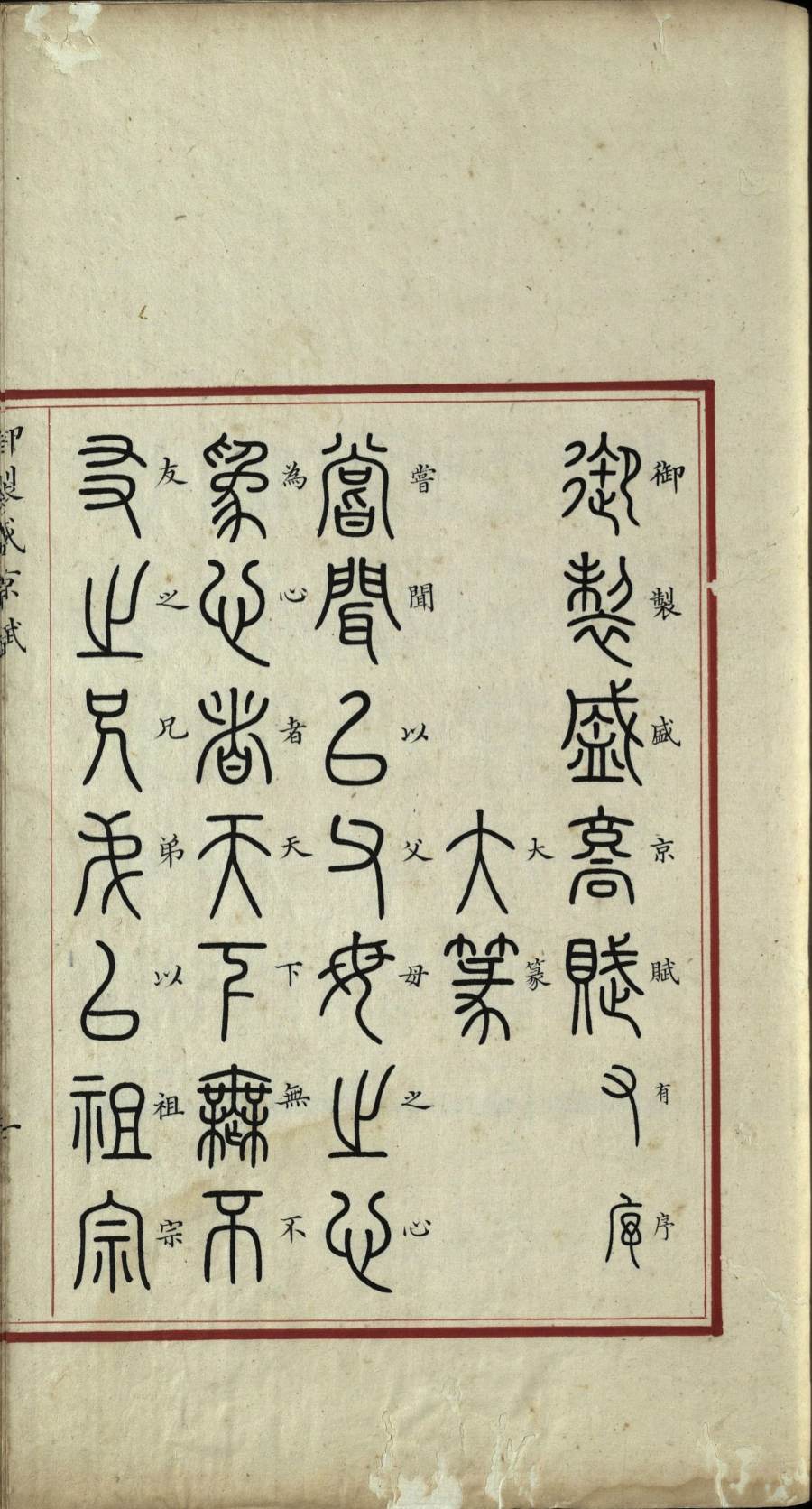
《盛京赋》是清乾隆帝东巡盛京谒陵祭祖后所撰,全文 3390 余字。为传播此赋,他令臣工广搜载籍,据援古法,撰写各体篆文,镌刻成《御制盛京赋》,一种篆体为一卷,内容相同,共三十二体,篆文为大字,边附小字释文。此内含清乾隆时期内府精写本(存十体)、内府刊本(存十五体)两种。
《御制盛京赋》是乾隆帝所撰最著名的一篇诗赋,乾隆八年(1743 年)九月乾隆皇帝奉皇太后经由热河抵盛京谒陵祭祖,冬 10 月抵达盛京(今沈阳)故宫大政殿,诗兴大发,书就《盛京赋》。此书系乾隆皇帝令臣工广搜载籍,据援古法,撰写各体篆文,镌刻成书。三十二体篆文名为:玉筋篆、奇字篆、大篆、小篆、上方大篆、坟书篆、倒薤篆、穟书篆、龙爪篆、碧落篆、垂云篆、垂露篆、转宿篆、芝英篆、柳叶篆、鸟迹篆、雕虫篆、麟书篆、鸾凤篆、龙书篆、剪刀篆、龟书篆、鹄头篆、鸟书篆、科斗篆、缨络篆、悬针篆、飞白篆、殳篆、金错篆、刻符篆、钟鼎篆。各篆所书字体婀娜秀丽。每部后面都附有 “篆书缘起”,考述该种篆体的创制或流转的情况。
在这三十二种篆体中,大部分为象形篆或异体篆。象形是汉字最初的造字方法,也是六书的基础。秦以前的文字属于初创阶段的文字,秦统一为小篆,初次实现了汉字的规范化。由于隶书的广泛应用,篆书渐渐失去了实用价值。东汉以后,篆书日渐衰微。唐以后,真行草大行其道,篆书更加衰微。直到清代随着碑学的盛行以及甲骨文、金文的大量发现,篆书才重新被书界所重视,并且出现了邓石如这样的篆书大家。此书 32 种篆体大部分都源自前代书体,包括古代象形篆书的精华。